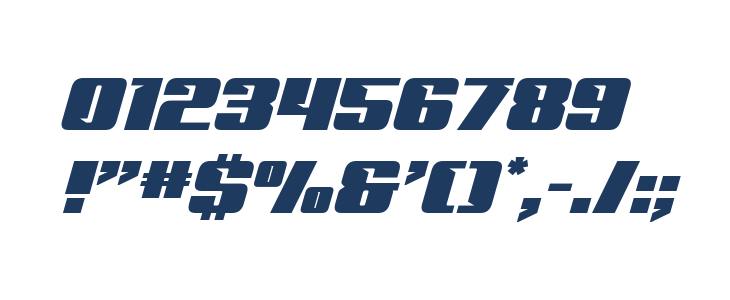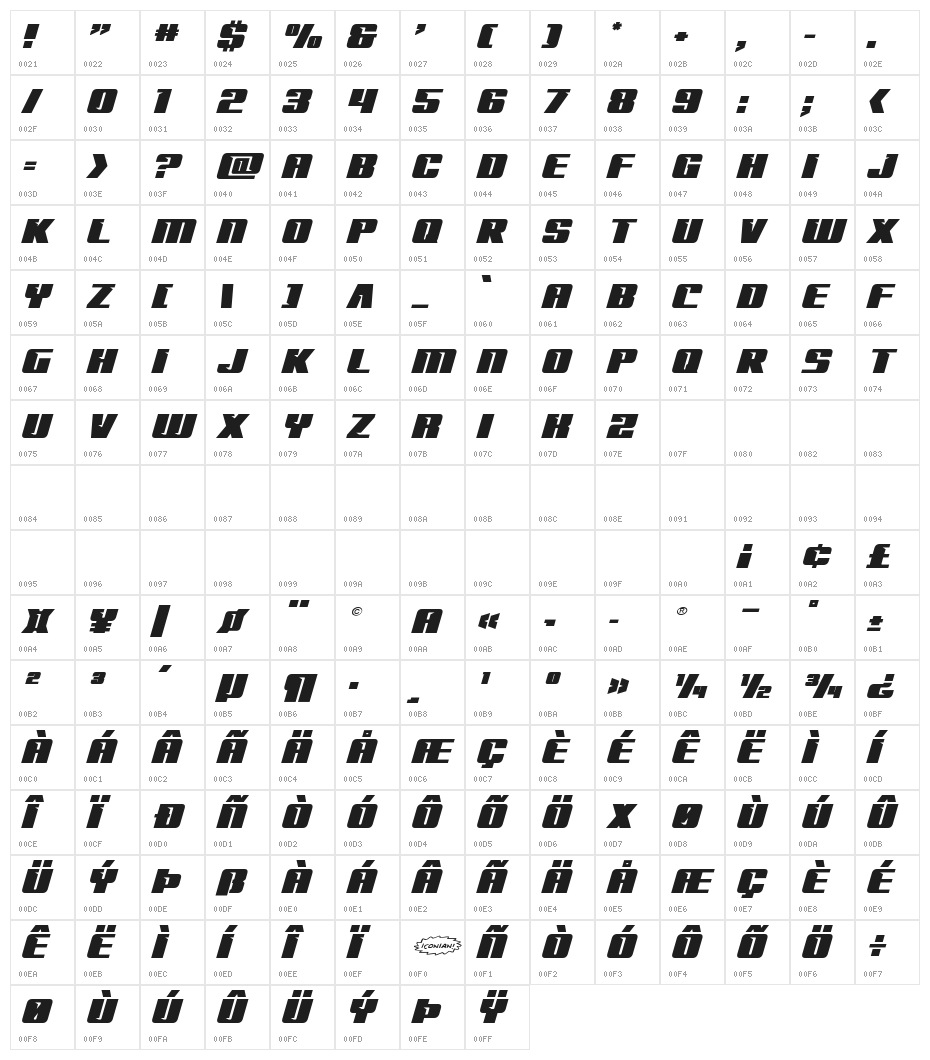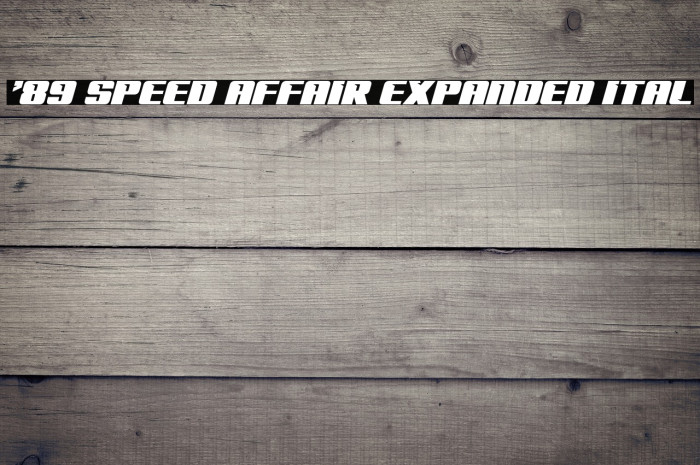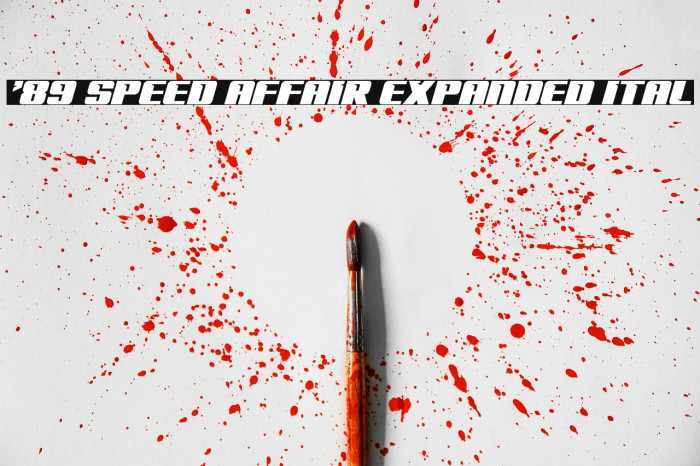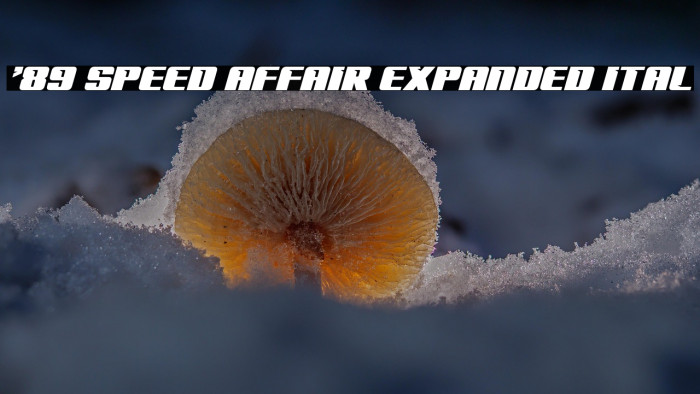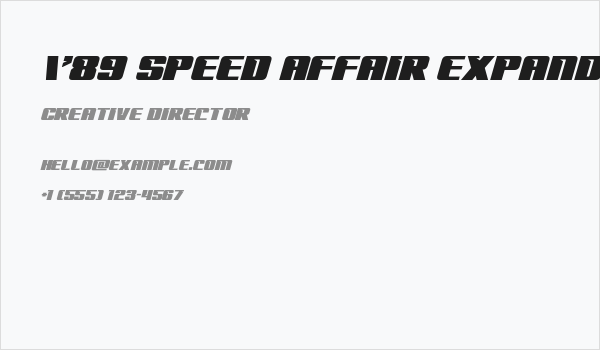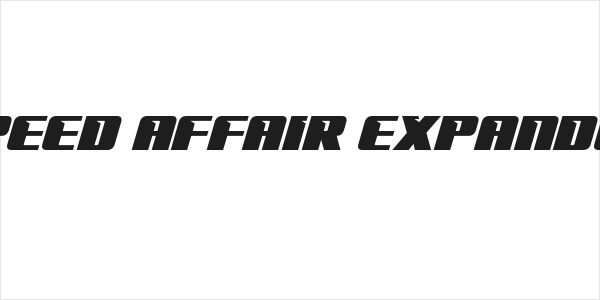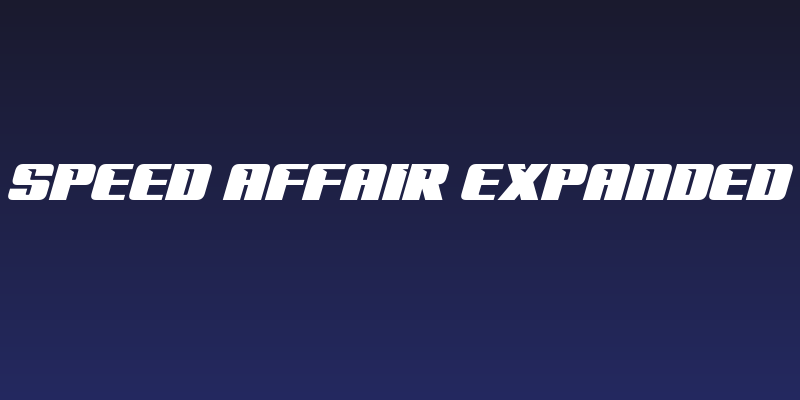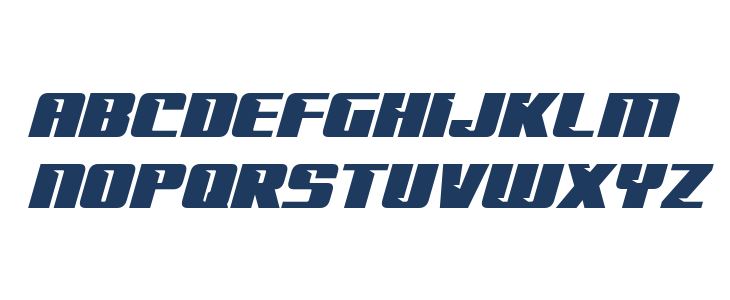
'89 Speed Affair Expanded Ital Font
| مشاريع مقترحة | Ideal for use in automotive branding, sports team logos, dynamic posters, and futuristic-themed designs. |